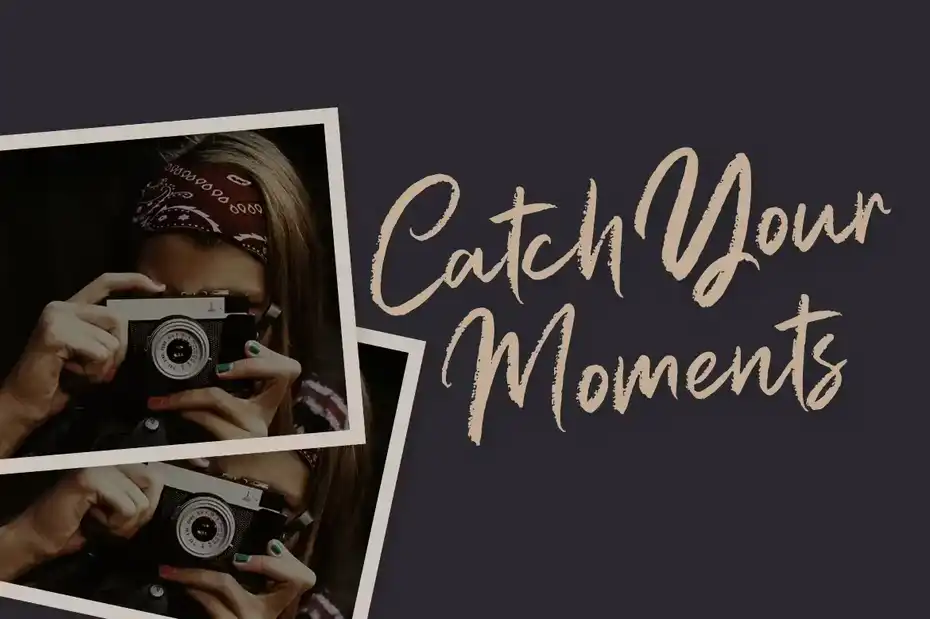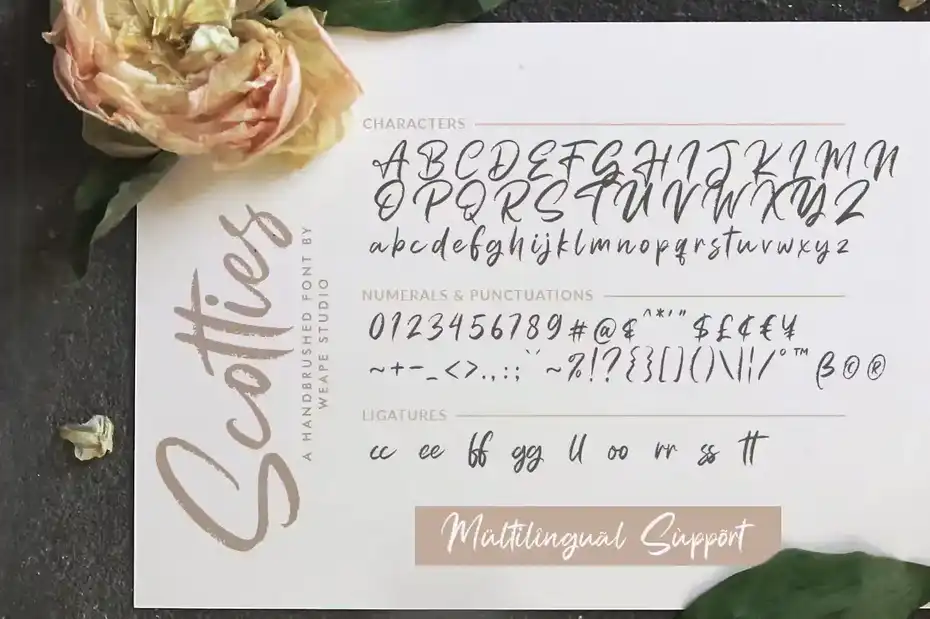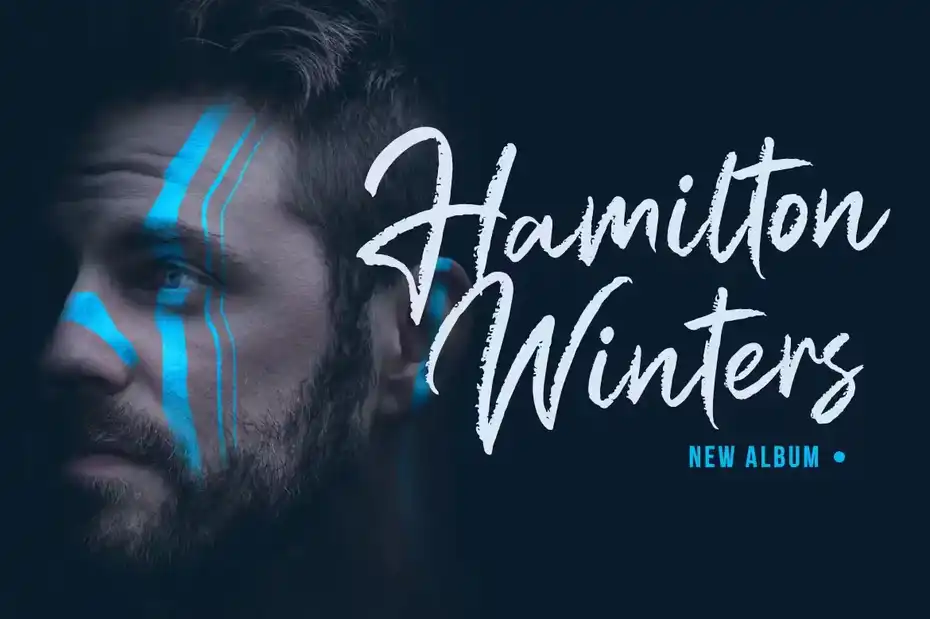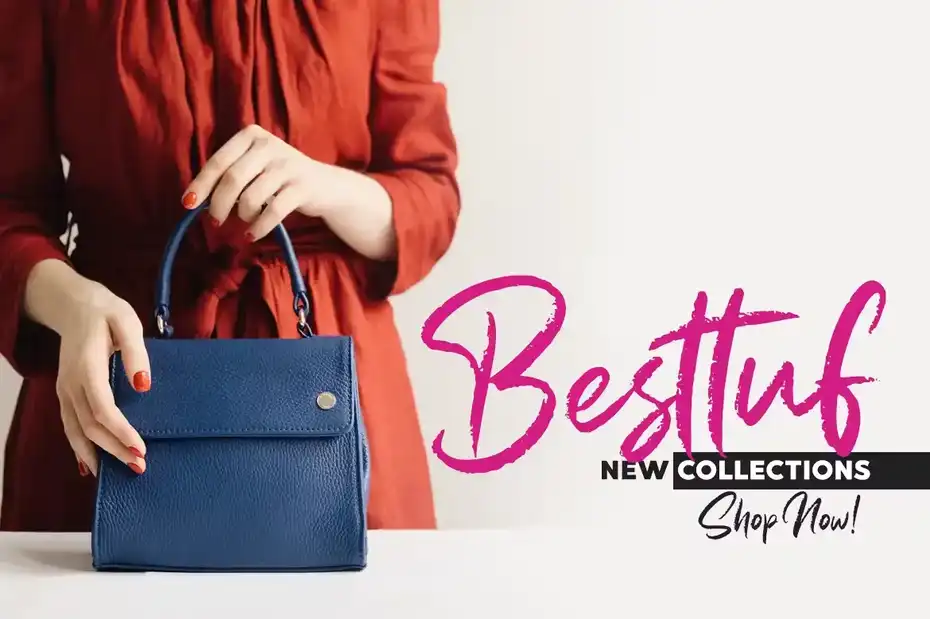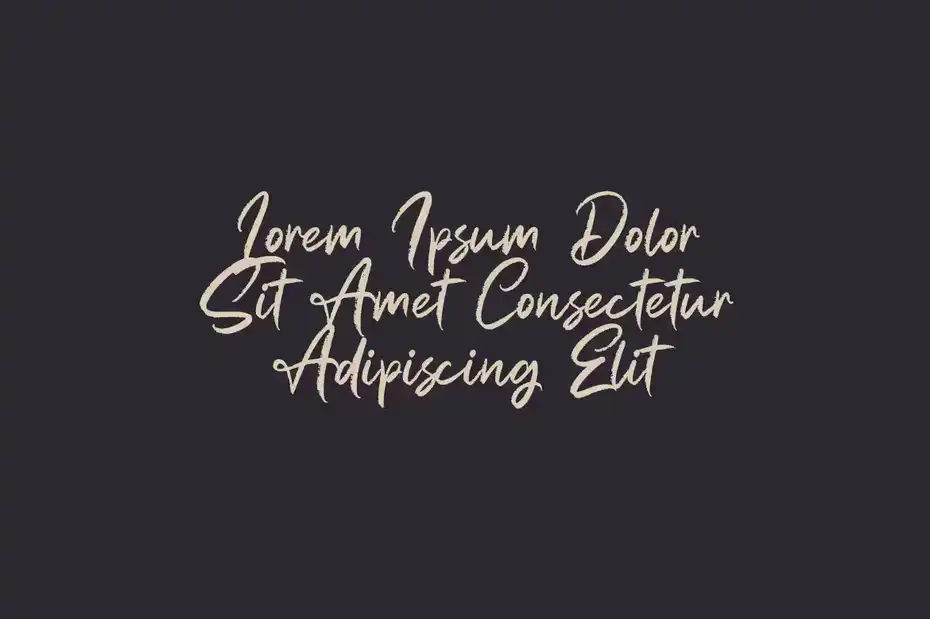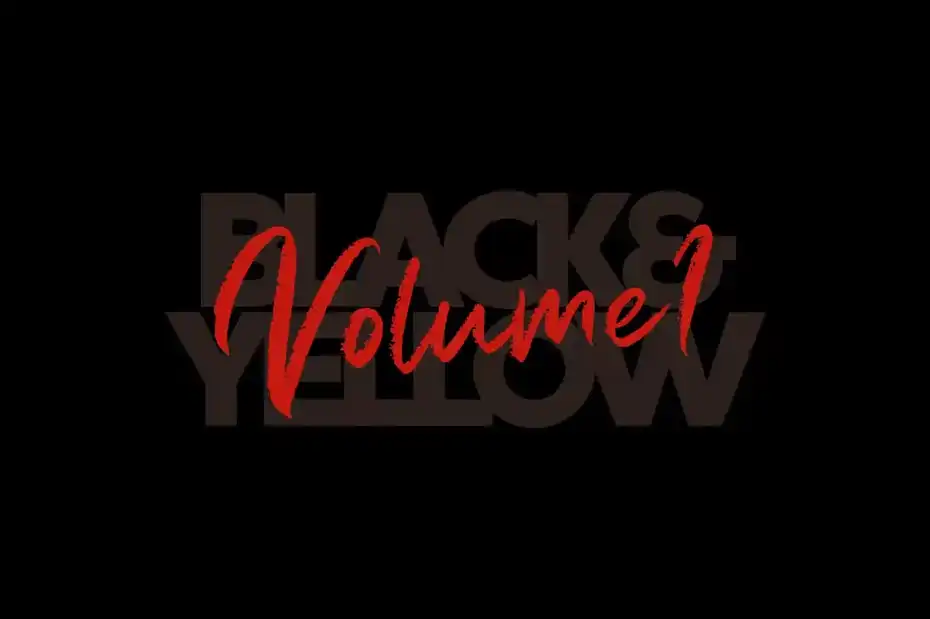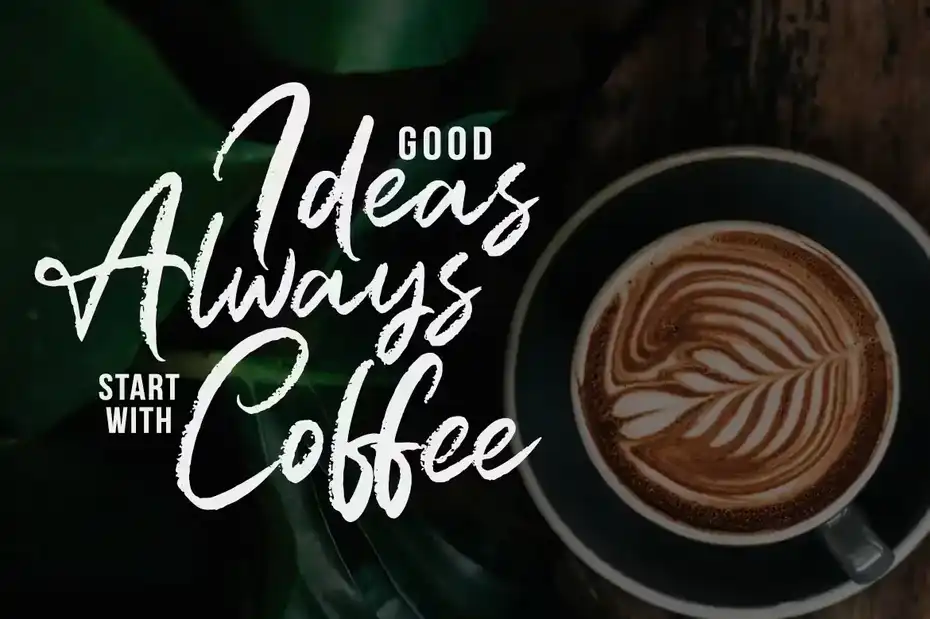
دانلود فونت انگلیسی دست نویس Scotties – Hand Brushed Font
فونت انگلیسی دست نویس Scotties – Hand Brushed Font : این مجموعه شامل یک فونت انگلیسی دست نویس است که برای امضا، برندینگ، کارت عروسی، مد و فشن، تایتل عکاسی، پوستر، شبکه های اجتماعی، بنر تبلیغاتی، جلد کتاب، بسته بندی، نقل قول های دست نویس، کارت های تبریک و تبلیغات مناسب میباشد.